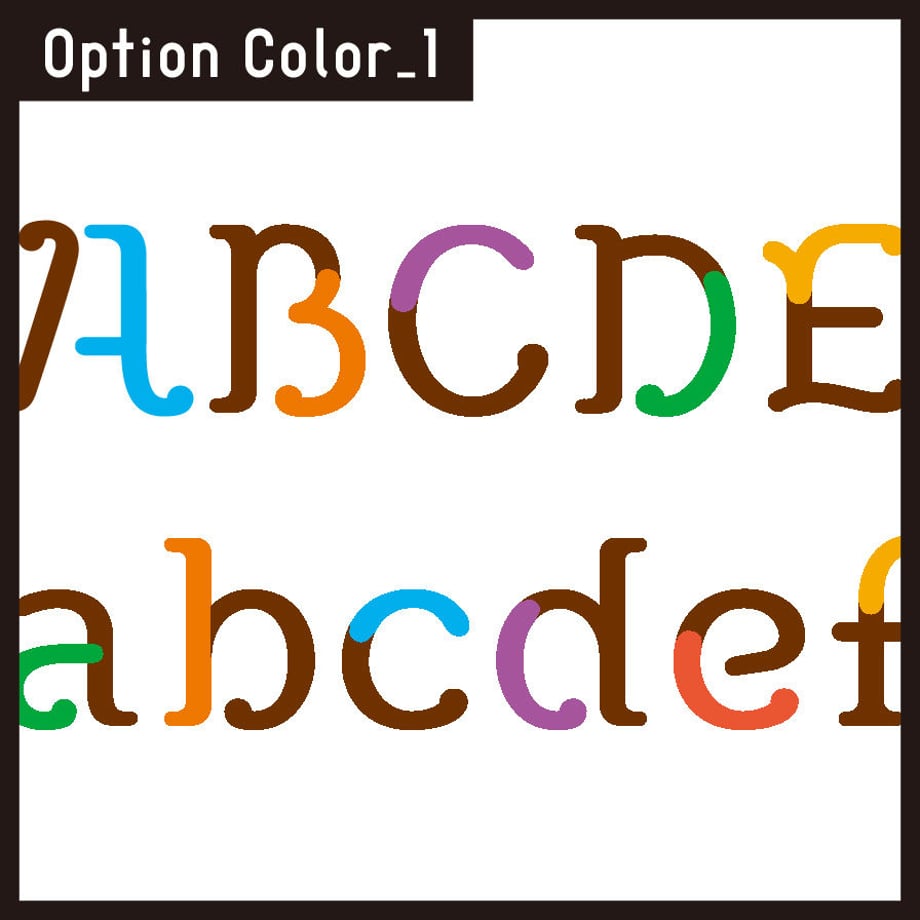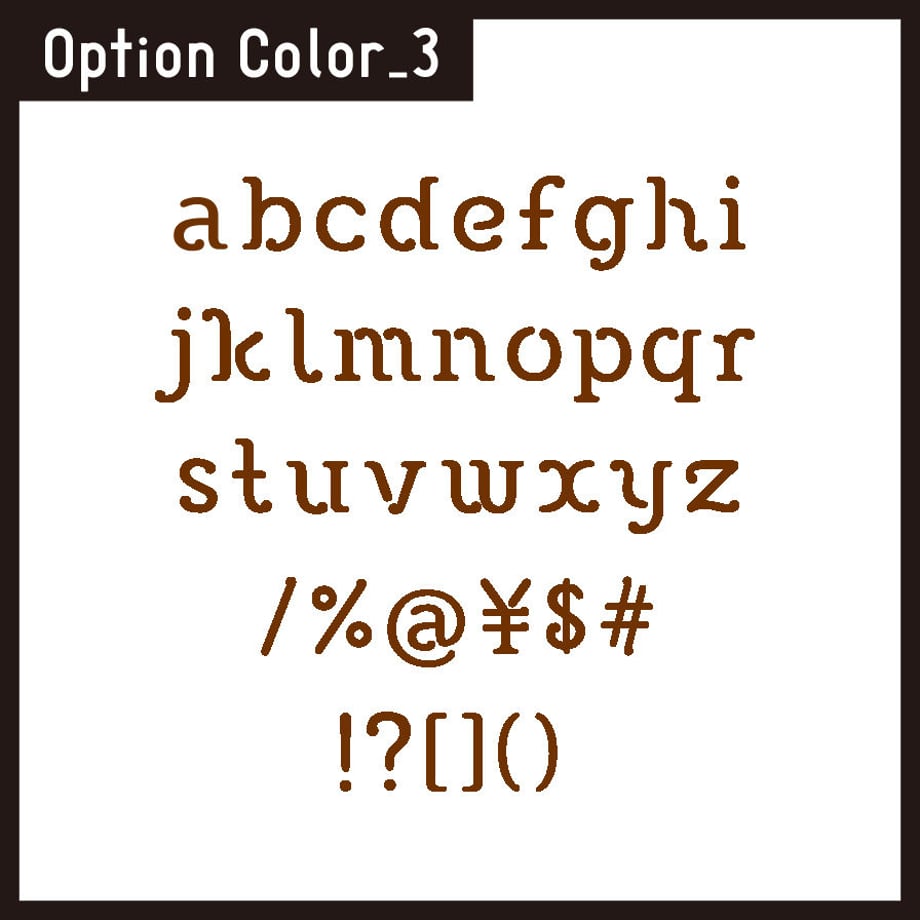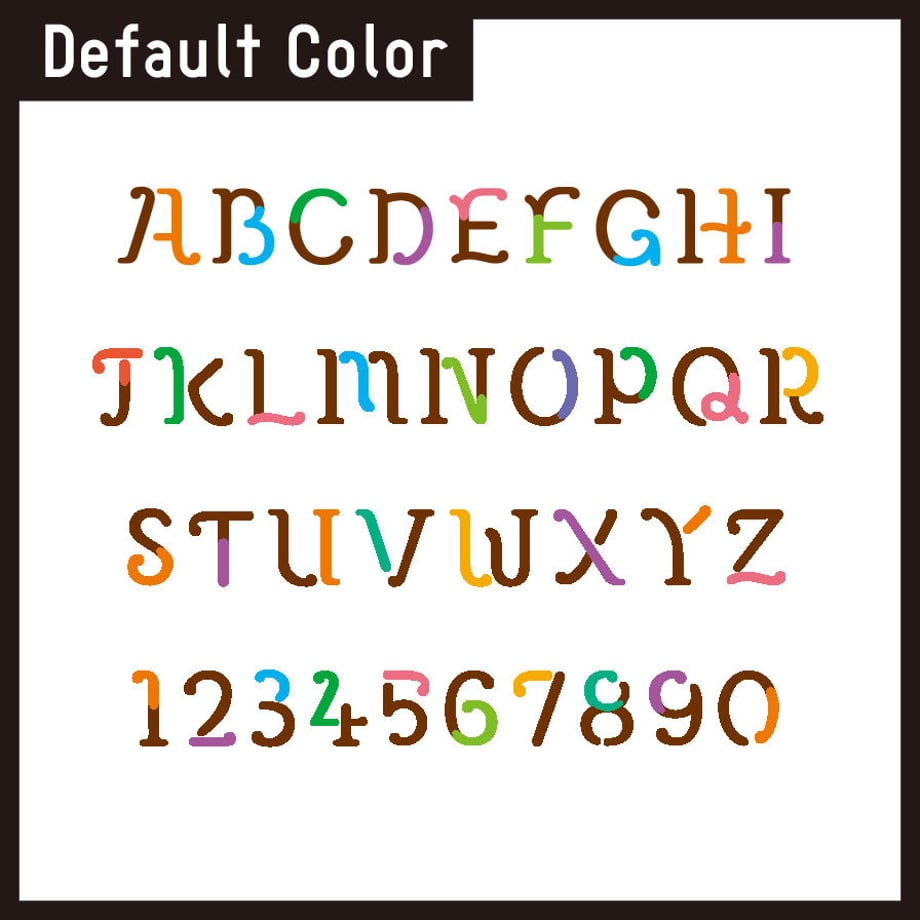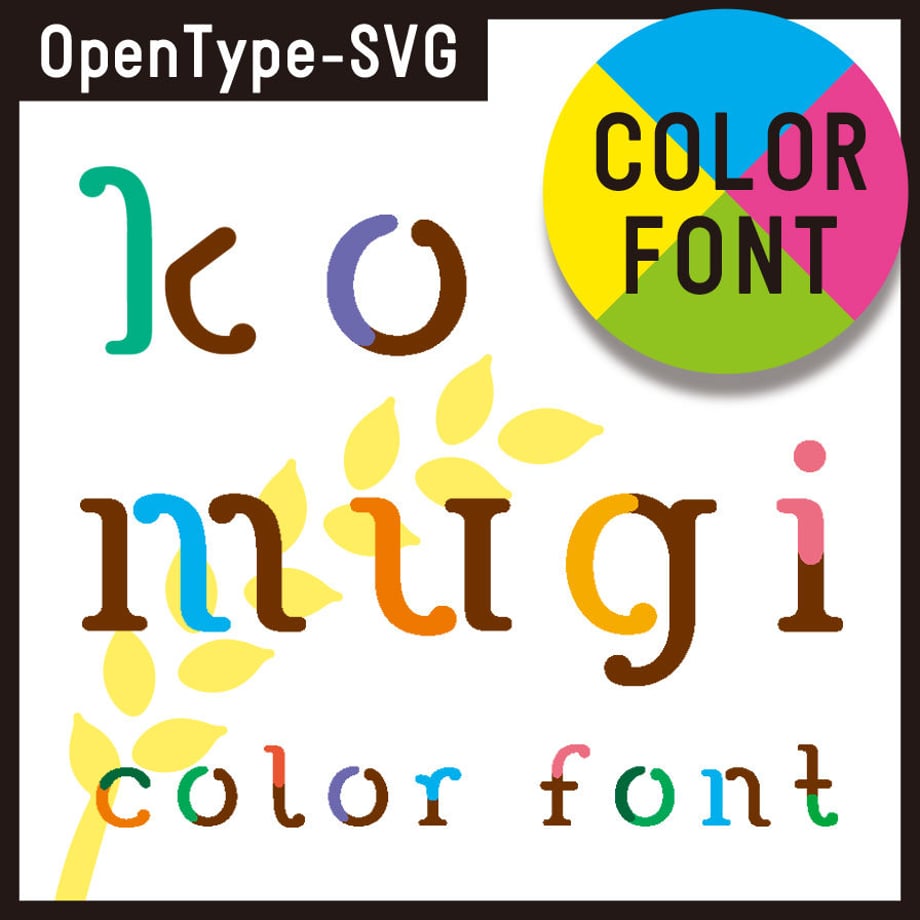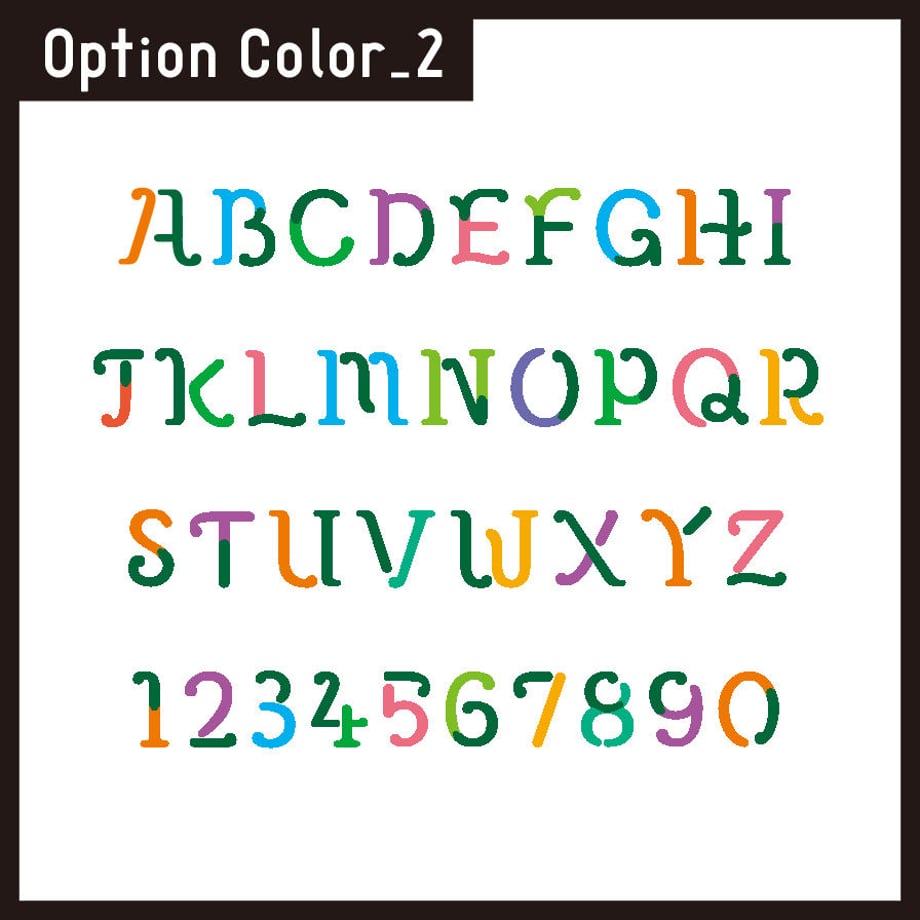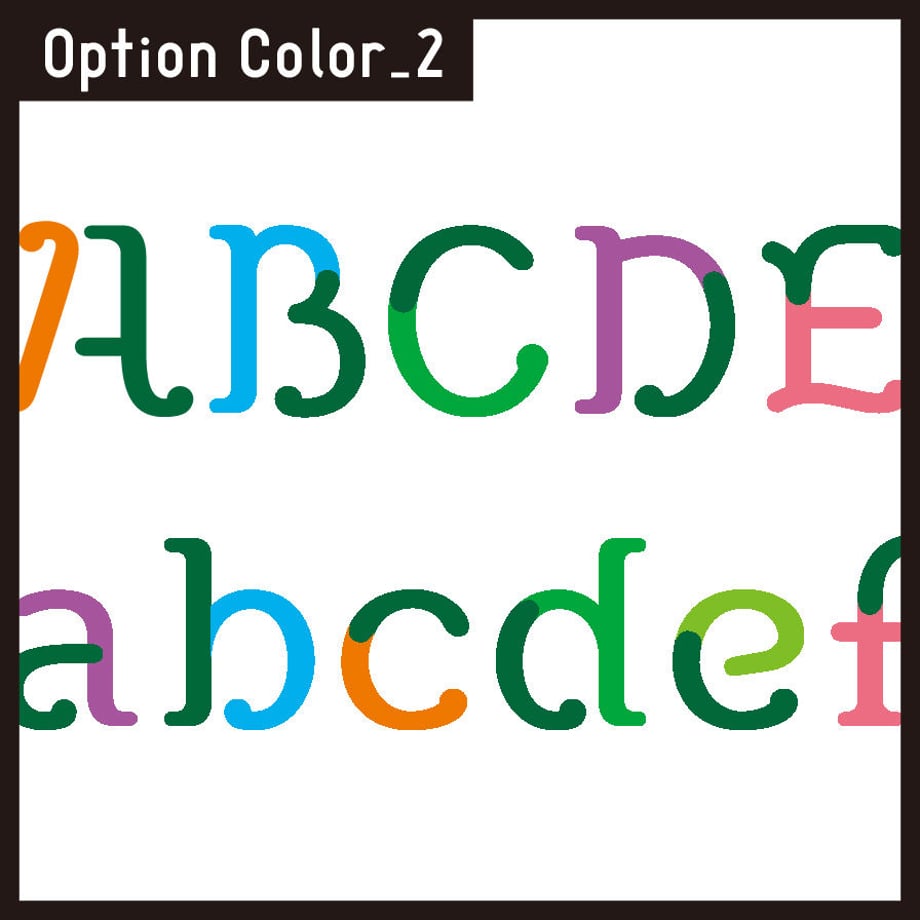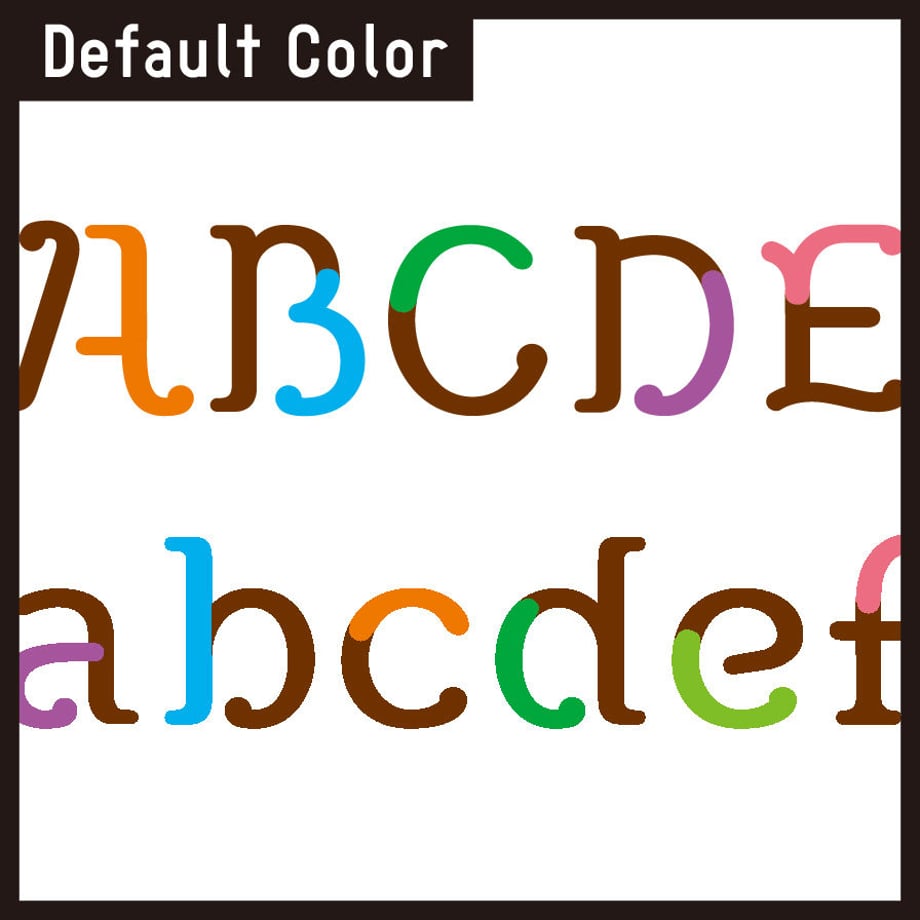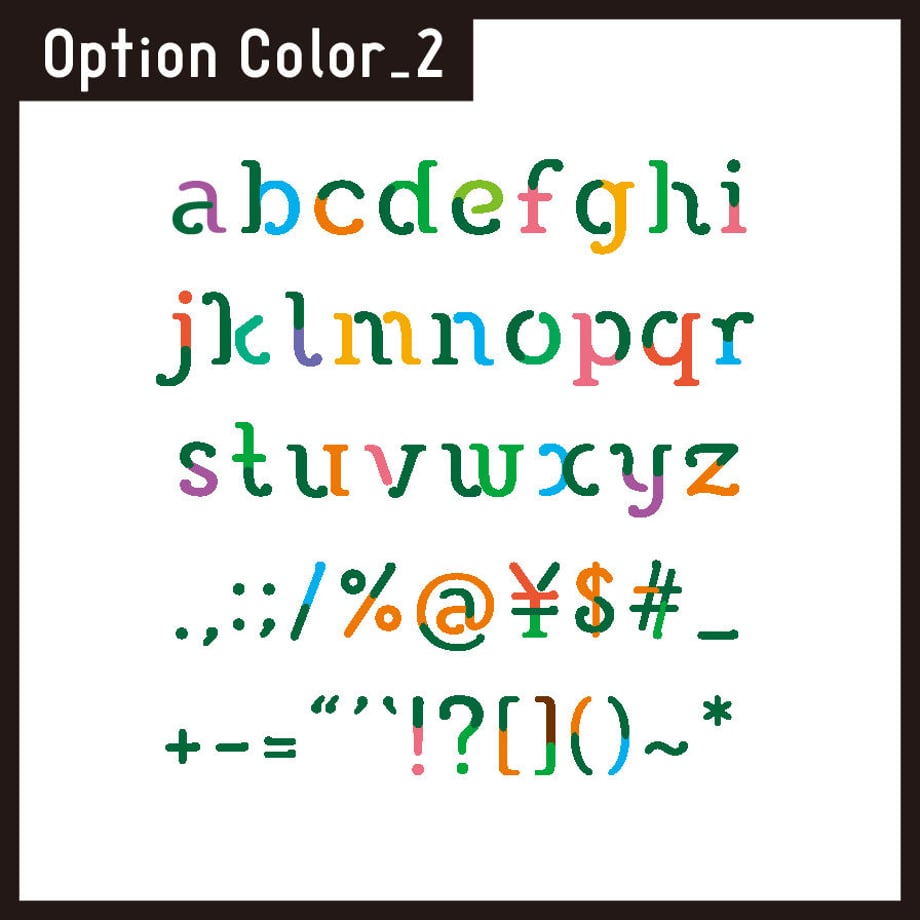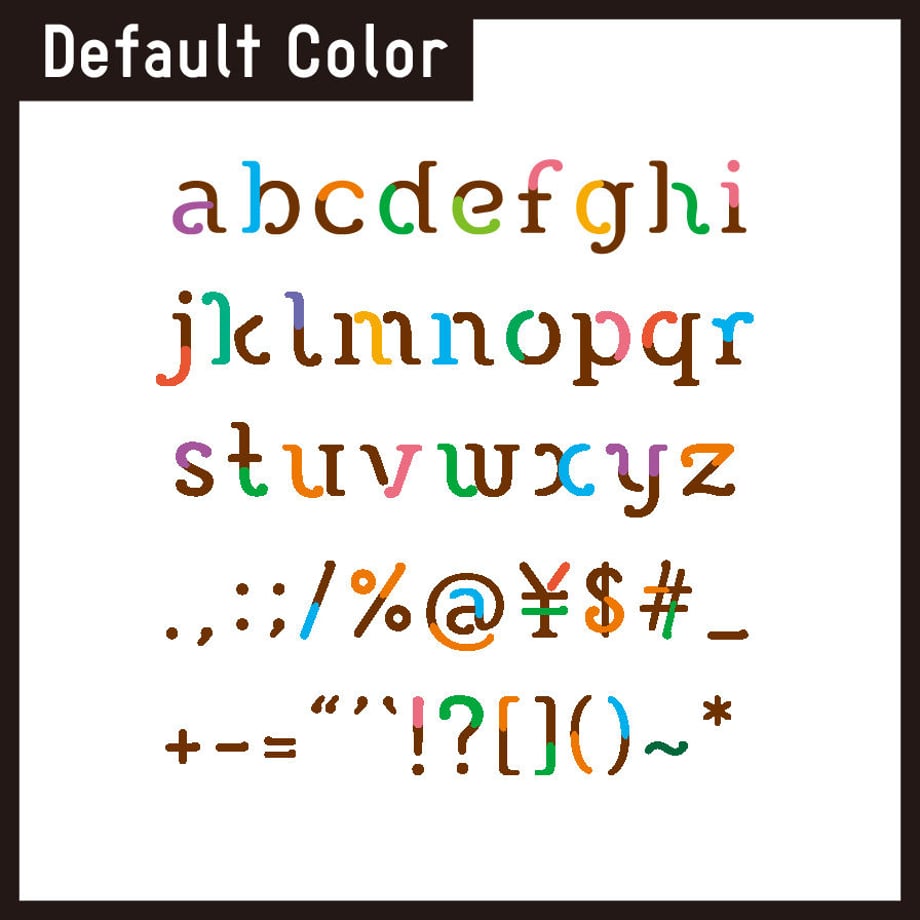
komugi color font(こむぎ カラーフォント)
現在Illustrator CC、Photoshop CCで使用可能なカラーフォント(OpenType-SVG フォント)です。ひとつのフォントの中に数種類のカラーやデザインがプログラムされていて、ポップアップ選択パネルから自由な組み合わせができます。アウトラインをかけて、色やデザインのカステムも可能なのであなただけのオリジナルデザインに生まれ変わらせることもできます。